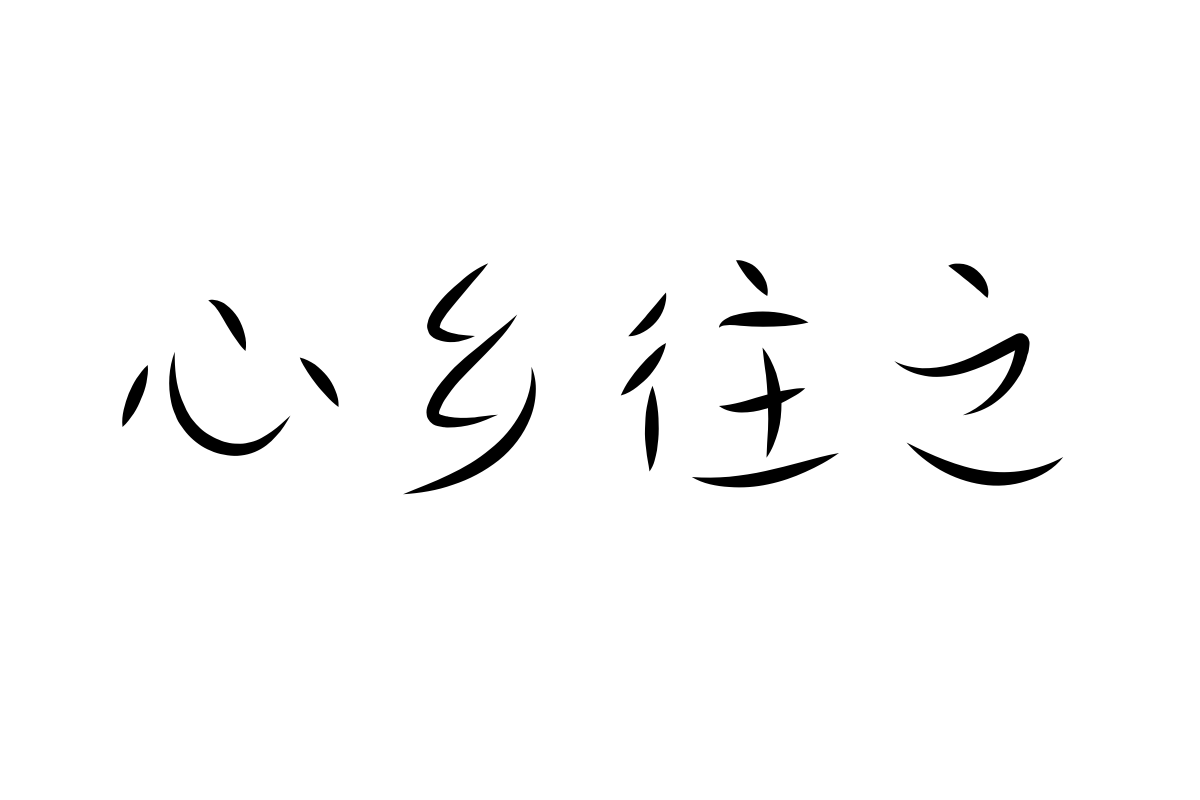
汉仪柳飘飘简是一款简约风格的中文字体,具有独特的书法风格和流畅的笔画。这款字体适合用于各种需要展示文字美感的场合,如网页设计、平面设计、广告宣传等。
字体特点:
1. 线条流畅:汉仪柳飘飘简采用了流畅的线条,使得文字看起来更加自然和美观。
2. 字形独特:这款字体的字形独特,具有浓厚的书法韵味,给人一种优雅的感觉。
3. 易读性强:汉仪柳飘飘简的笔画简单易懂,适合各种年龄层次的人群阅读。
4. 适用范围广:这款字体适用于各种需要展示文字美感的场合,如网页设计、平面设计、广告宣传等。
总之,汉仪柳飘飘简是一款非常实用的中文字体,适合用于各种需要展示文字美感的场合。